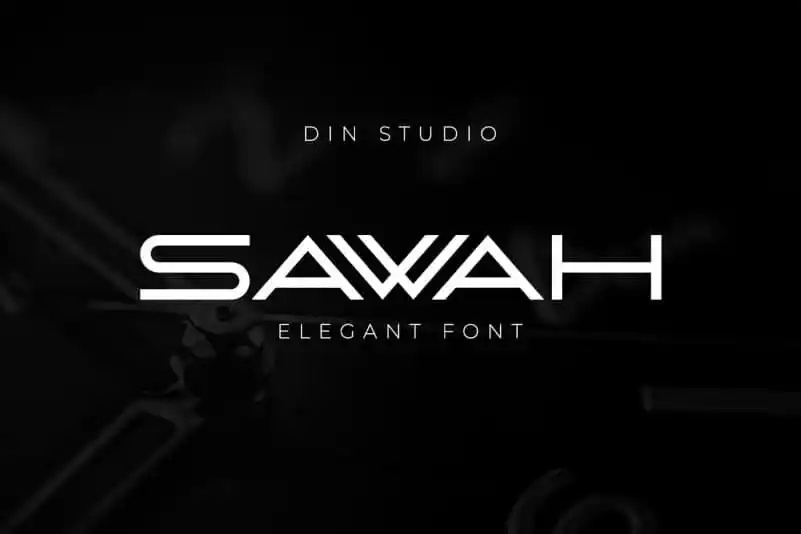
Sawah Display Font – Download Grátis
Sawah Display Font é uma fonte de exibição versátil com seu acabamento limpo e refinado. Suas letras maiúsculas redondas enfatizam a sensação moderna e ordenada. A tipografia como um todo é geométrica, promovendo ordem e alinhamento entre as letras. Esta fonte celebra formas abstratas em toda sua beleza diversificada. Ela se destaca em diversos contextos, sendo ideal para logomarcas, branding e citações. É a melhor escolha para qualquer projeto que exija um acabamento de alta qualidade e elegância moderna.